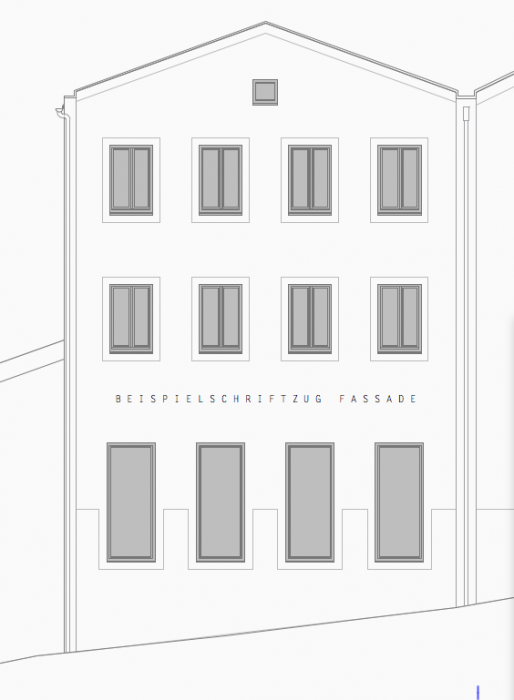
Fassadenschriftzug
ich bin architekt und soll einen über eine fassade laufenden schriftzug gestalten. die lettern sollen einzeln in metall hergestellt werden (wahrscheinlich aus dickem blech geschnitten) und auf der putzfassade einzeln befestigt.
ich habe mich (für einen laien) schon relativ viel mit typografie befasst. trotzdem gibt es hier sehr viele, die das besser wissen.
also:
wie geht man da vor?
wen könnte es hier auf dem land geben, der noch schriften entwerfen kann? kann man eine "computerschrift" als grundlage verwenden? muss man die lettern nachbearbeiten/anpassen? wie setzt/spationiert man den schriftzug dann? welche regeln/bücher gibt es dafür?
der ausdruck soll eher klar/klassich/geometrisch sein, in richtung avant garde, futura, etc.
je eigenständiger es am ende ist desto besser aber.
schön, dass Du hier nachfragst, so wird dann künftig so was hier vermieden, hoffe ich.
Bevor sich die Experten zu Wort melden, wäre vermutlich ein wenig mehr Information der Qualität der Antworten förderlich, z.B. was für eine Art von Gebäude, welche Fassadenanmutung, welche Nutzung, Neubau oder Entstehungsjahr, Beschriftung mit Eigenname des Nutzers oder Bezeichnung des Gebäudes, falls Nutzername, hat dieser ein Corporate Design, das Berücksichtigung finden soll, und noch Sachen, die mir als Amateur nicht einfallen, Dir als Architekt aber schon, um das Gebäude, seine Umgebung und somit den Kontext der Beschriftung zu beschreiben.
Je besseren Input Du gibst, umso bessere Antworten wirst Du erhalten.
Eine erste Einschätzung zur Nutzung von "Computerschriften": Das sollte in der von Dir angedeuteten klassisch-geometrischen Richtung imho kein Problem darstellen.
es ist ein neubau, putzfassade mit lochfenstern.
der schriftzug läuft breit, über ca 2/3 der fassade.
das gebäude ist öffentlich, die ci des nutzers zu unterirdisch um in frage zu kommen.
so sieht es bisher in den plänen aus:
Jetzt ist der Architekt gefragt … soll der Schriftzug das schmale Hohe aufgreifen oder möchtest du einen Bruch durch den Schriftzug? Mir schwebt auf die Schnelle was feines Geometrisches / Rundes vor, als Kontrast zur nüchternen schmalen Fassade und den hohen schmalen Fenstern im EG.
Ich denke die Wortmeldung aus Ostritz ist ein sehr wertvoller Hinweis. Im übrigen sind Sie so gut wie garantiert auf der sicheren Seite, wenn ein ausgewiesener Schrift(font)gestalter als Berater oder Entwerfer hinzugezogen wird. Da tummeln sich hier gewiß genug Kollegen, die das machen könnten.
Ich begrüße es sehr, wenn Sie sich als Architekt Gedanken über die Schrift am Bau machen. Oft ist das nämlich leider nicht der Fall, selbst bei ambitionierten Projekten in 1A-Lage: ich habe erst vorige Woche einen geschätzten Architekten rüffeln müssen, weil er ein todschickes neues Bürohaus im Stil der klassischen Moderne (Trias, Leipziger Innenstadt) mit Helvetica-Flachblech beklebt hat, was ja nun gar nicht geht.
Gegen die Helvetica ist nichts zu sagen, außer daß sich manche Designer (aus mir nicht nachvollziehbaren Gründen) über sie erregen können, während andere sie verwenden wie jeden anderen Klassiker auch. Es kommt immer und überall auf die Anwendung an. In den meisten heute verwendeten Druckschriften ist die Entstehungszeit unsichtbar geworden. Ob ein Haus und ein Schnitt und ein Satz einer Schrift (Anwendung) zusammenpassen, drückt sich nicht in zwei Begriffen aus. Wenn es gut gemacht ist, kann eine Helvetica an fast jeden Baustil geheftet werden.